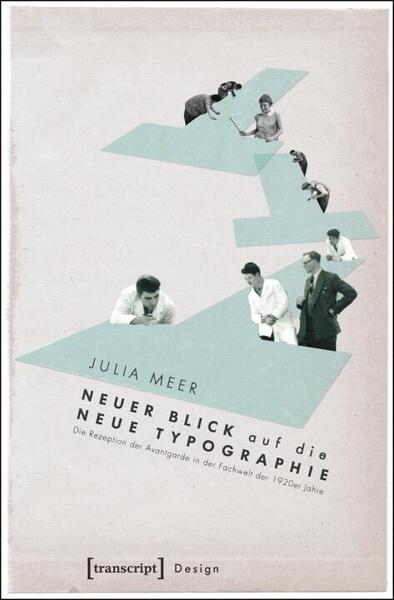
Neuer Blick auf die Neue Typographie
Julia Meer stellt in dieser design- und kulturwissenschaftliche Arbeit die bisherige Rezeptionsgeschichte des »Mythos Neue Typographie« in Frage und arbeitet zugleich die frühe Professionalisierung des Grafik-Designs auf.
Die bisherige Darstellung der Entwicklung der modernen Typografie ist stark an den Aussagen und Arbeiten der künstlerischen Avantgarde der 1920er Jahre orientiert. Thesen und Rezeption wurden von den Protagonisten oft unkritisch übernommen. Durch eine systematische Auswertung von Fachzeitschriften zwischen  1900 und 1933 zeigt Julia Meer in diesem Buch auf, dass die Thesen der Neue Typographie weder so neu waren wie behauptet, noch aufgrund ihrer vermeintlichen Modernität abgelehnt wurden. Vielmehr wurden sie früh von den Fachleuten gefördert und zu einem werbewirksamen Stil weiterentwickelt. Damit ging ein Prozess einher, in dem sich einige Protagonisten der Avantgarde von Künstlern zu Designern professionalisierten. Die Studie eröffnet neue Perspektiven auf die Wirkungsweise und Verbreitungsprinzipien von Design und das Selbstverständnis von Designern. Und sie rückt ein bislang in der Designliteratur oft verzerrt dargestelltes Bild auf die Neue Typographie wieder gerade.
Inhalt:
• Die Avantgarde auf dem Prüfstand – das Innovationspotential der Neuen Typographie
• Was ist angeblich »neu« an der »Neuen Typographie«?
• Wie »neu« ist die »Neue Typographie«? – Traditionslinien und Parallelen
• Kritische Forschung oder praxisorientierte Nacherzählung? – Mängel und Potential der Designgeschichtsschreibung
• Implikationen und Manipulationen – Problematisierung der bisherigen Darstellung der Geschichte der Neuen Typographie
• Revision der Geschichte des Grafik-Designs – Voraussetzungen kritischer Designgeschichtsschreibung
• Rezeption der Neuen Typographie in der typografischen Fachwelt 1924–1933
• Konservativ-bürgerliche Anti-Avantgardisten? – Ablehnende Reaktionen auf die Neue Typographie
• »Sieg der Avantgarde«? – Alternative Interpretation der Durchsetzung moderner Formprinzipien
• Eine Frage der Disziplin – Neubewertung der Avantgarde durch das Prisma »Professionalisierung«
• Vom avantgardistischen Künstler zum Designer? – Die Professionalisierung der Neuen Typographen
• Professionalisierung – Eine neue Perspektive auf die Designgeschichte
• Fazit: Neuer Blick zeigt neues Bild – eine andere Rezeptionsgeschichte der Neuen Typographie
Untertitel: Die Rezeption der Avantgarde in der Fachwelt der 1920er Jahre
Autor(en): Julia Meer